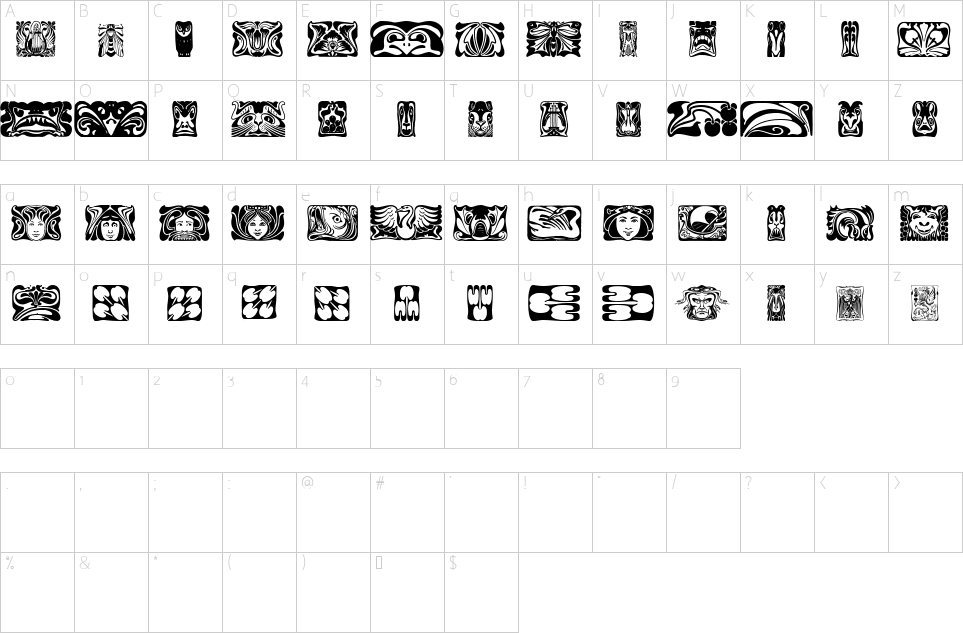
A fonte Jugendstil Ornamente é um encantador conjunto de caracteres que remete aos anos de renovação estilística conhecidos como Jugendstil, ou estilo jovem, que dominou a arquitetura e a design gráfico no início do século XX. Este conjunto de fontes apresenta uma rica variedade de ornamentos e linhas elegantes, projetado por Dieter Steffmann. Suas linhas fluidas e formas arredondadas proporcionam um toque moderno e contemporâneo, tornando-a uma escolha perfeita para qualquer projeto que busque um enfoque visual único e sofisticado. Ideal tanto para os projetos digitais quanto para impressão, a Jugendstil Ornamente font é uma excelente maneira de dar um toque personalizado a seus materiais gráficos. Seu design elegante e harmonioso, combinado com sua grande variedade de ornamentos, o torna uma escolha ideal para designers, freelancers, e até mesmo amantes do design, que buscam adicionar um toque especial a suas criações. Com o Jugendstil Ornamente, você pode explorar os limites da criatividade e transformar simples ideias em verdadeiros trabalhos de arte digitais.